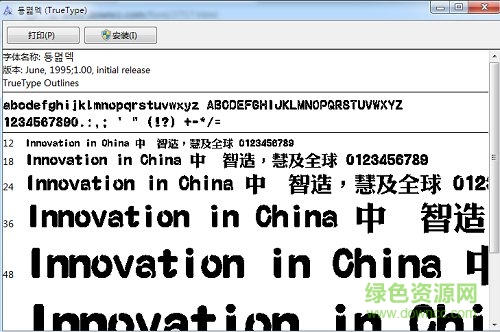
富漢通中仿黑字體
富漢通中仿黑字體是一款字形美觀的電腦字體,表現(xiàn)為寫法方正,剛正不阿,適合作為報紙、廣告頁標(biāo)題使用,字體優(yōu)雅,自帶加粗特效,有需要的朋友可以下載使用!
富漢通中仿黑字體簡介
富漢通中仿黑字體是一款房黑體字體打造的中文字體,沒有襯線裝飾,筆劃粗壯有力,撇捺等筆畫不尖,使人易于閱讀,用途廣泛,文字排版、海報廣告設(shè)計、美術(shù)設(shè)計等方面都可以使用!